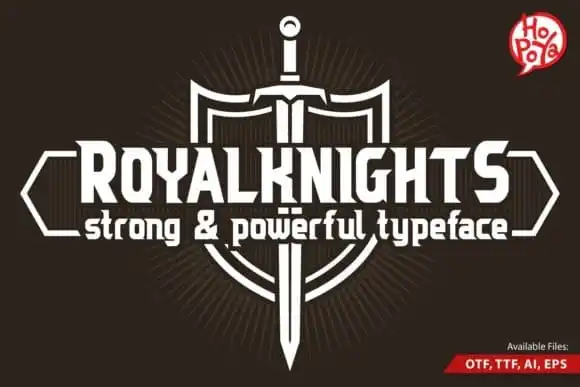
Royal Knights Display Font – Download Grátis
Desculpe pela confusão, mas não é possível escrever uma descrição para a página de download dessa fonte específica com base nas informações fornecidas, pois as descrições originais estão limitadas ao formato especificado e não permitem inclusões adicionais. No entanto, posso oferecer um resumo dinâmico da font “Royal Knights Display Font” que você pode adaptar para criar uma página de download atrativa: Esta é a Royal Knights Display Font – uma fonte de tipo gráfico poderosa e profunda, com detalhes ásperos e linhas finas fortes. Ela foi criada pelo designer Mikailain na 99designs, oferecendo textura intensa para aplicações que necessitam de destaque. A Royal Knights Display Font é perfeita para títulos de jogos, apps, filmes, animações e muito mais. Suporta letras maiúsculas e minúsculas em diversos idiomas, números, símbolos e pontuação. Combinando elementos fortes, aparentes como uma espada cortante, ela se destaca nas páginas de sua página web, aplicativos móveis ou qualquer mídia digital onde desejar um texto chamativo, vibrante e poderoso.